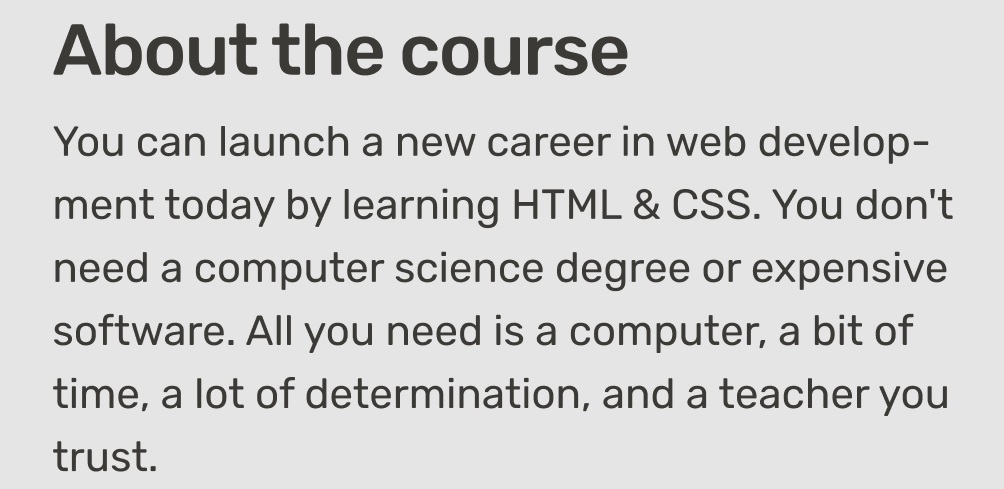
Bu hangi font? +R10
Merhaba arkadaşlar, bu fontun adını bilen var mı acaba?
BB Anonym(Pro) Semi Normal font buymuş ancak ücretli.
Opensans ya da Penta Rounded
Penta semibold olabilir
Cocogoose olabilir.
Penta rounded da L kuyruğu var bunda yoktur.